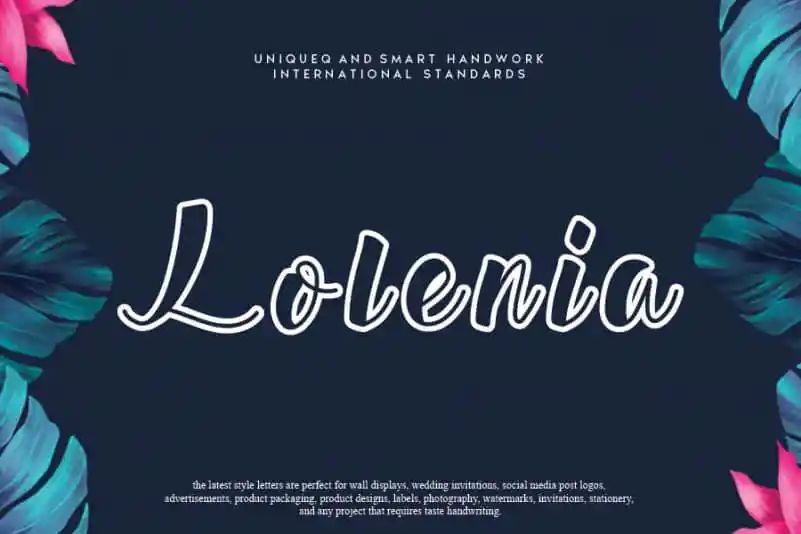
Lolenia Script Font – Fonte Grátis
Lolenia Script Font
Lolenia Script é uma elegante fonte display escrita a mão com linhas redondas que se destaca por sua versatilidade e simplicidade. Esta fonte é ideal para criar design de casamento incrivelmente profissional, arte de cartões bonitos, postagens nas mídias sociais impressionantes e muito mais. Com seu ar redondo e personalidade única, você pode criar experiências visualmente atraentes em diversos projetos de arte digital. Seja para aniversários de casamento, festas particulares ou simplesmente para aqueles momentos íntimos na web, Lolenia Script é uma escolha perfeita para tornar seus projetos mais atraentes e memoráveis. Descubra agora o charme de Lolenia Script e transforme suas criações digitais em obras que emocionam e encantam.